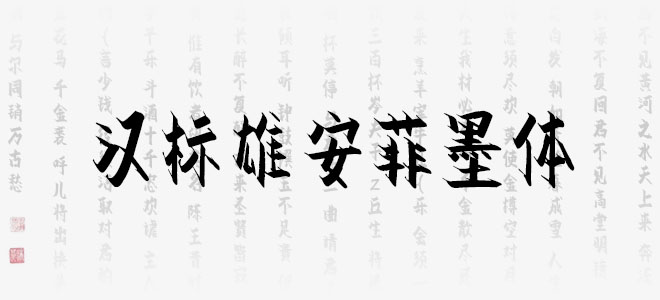
漢標(biāo)雄安菲墨體是用軟筆來書寫的軟筆字,字型既有楷體的挺拔,又有硬筆獨(dú)特的骨氣,是作者所書寫的眾多字體中,很喜歡的一款實(shí)用的字體。因?yàn)樽中挽`活,書寫感強(qiáng),所以特別適合廣告創(chuàng)意創(chuàng)作使用。歡迎喜歡漢標(biāo)雄安菲墨體的朋友前來下載使用。
漢標(biāo)雄安菲墨體